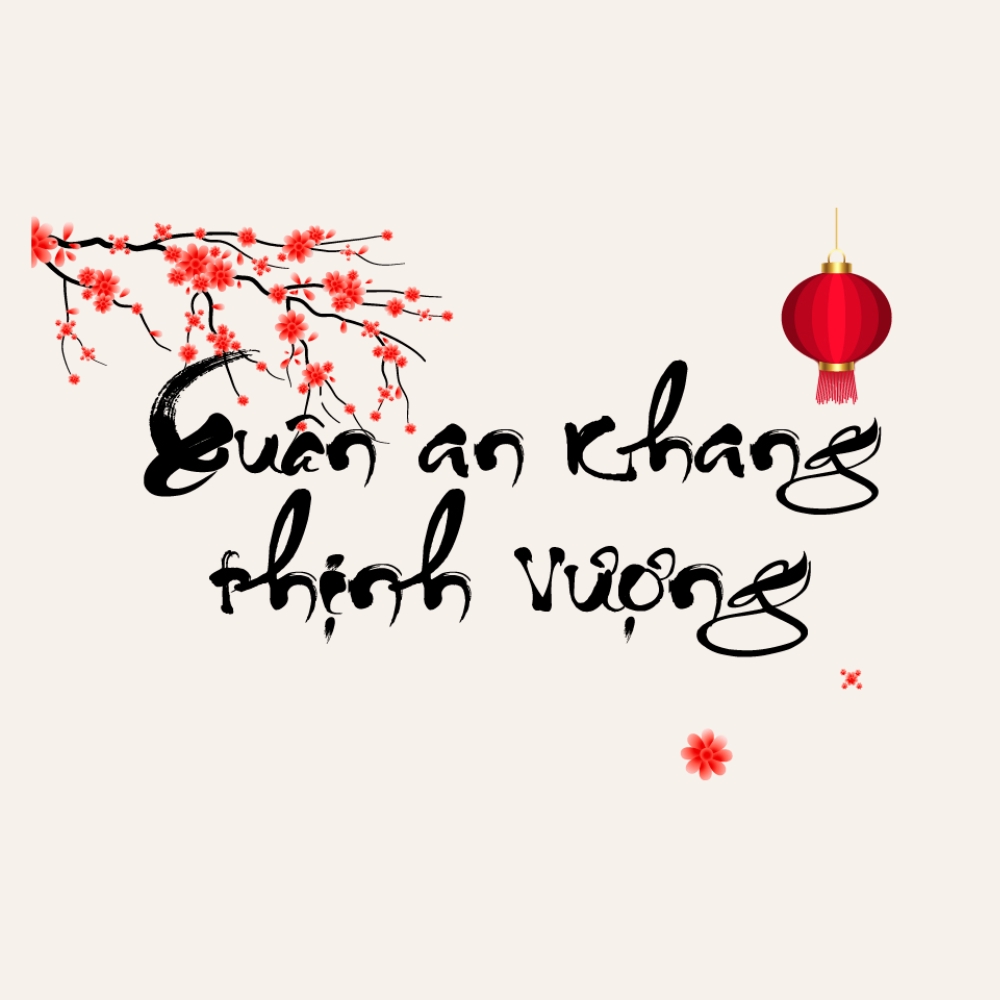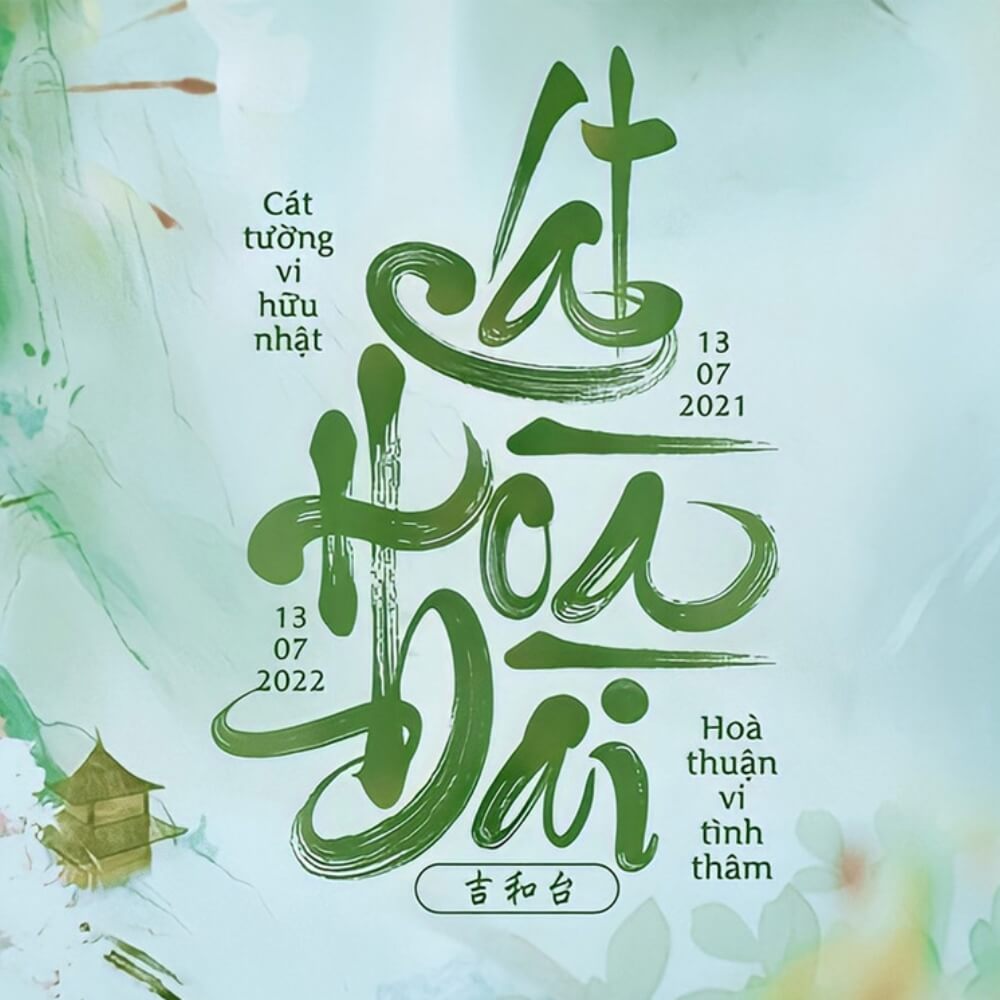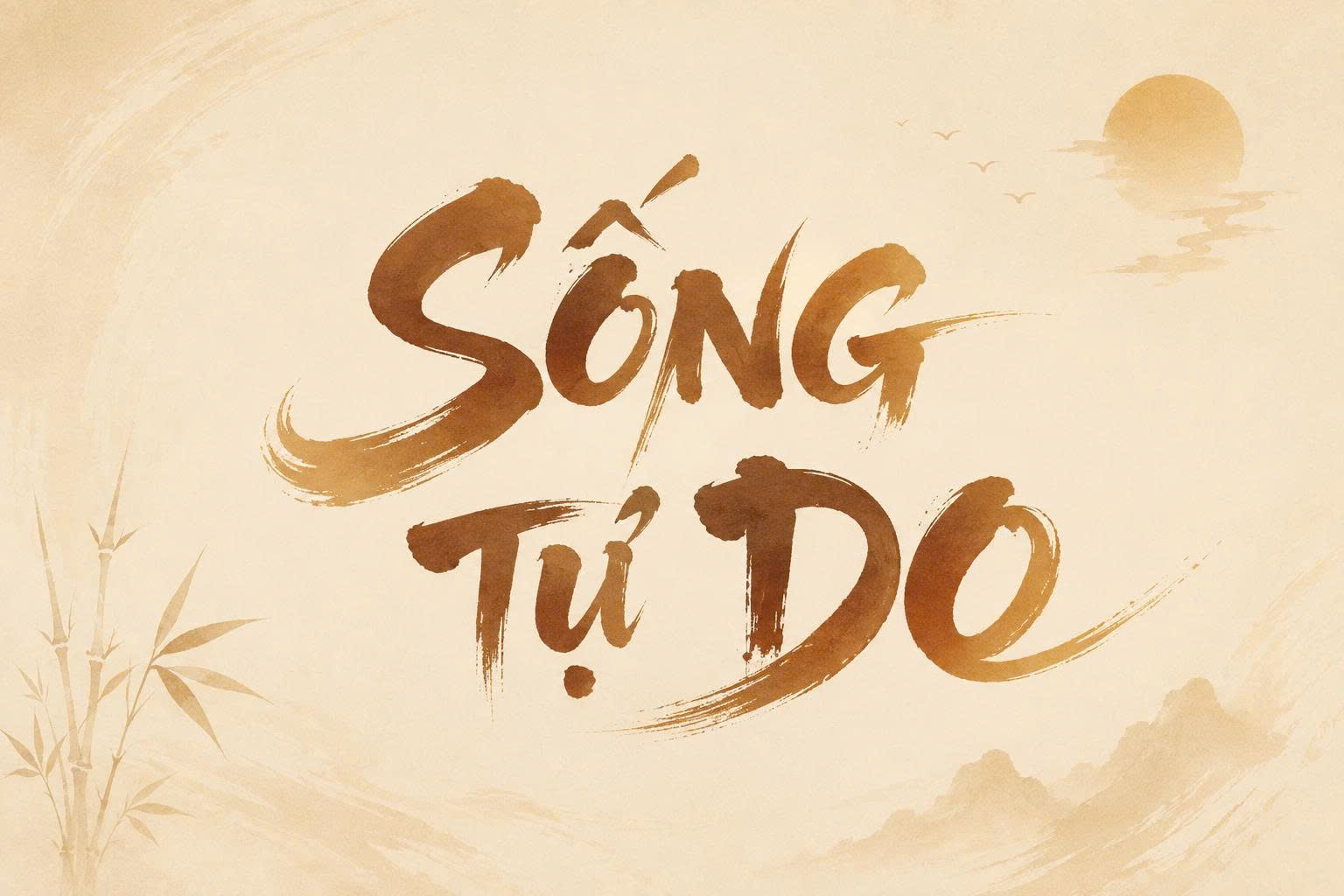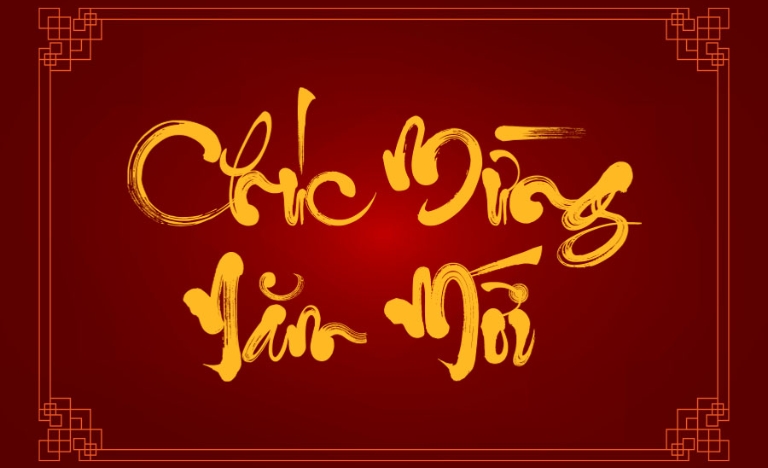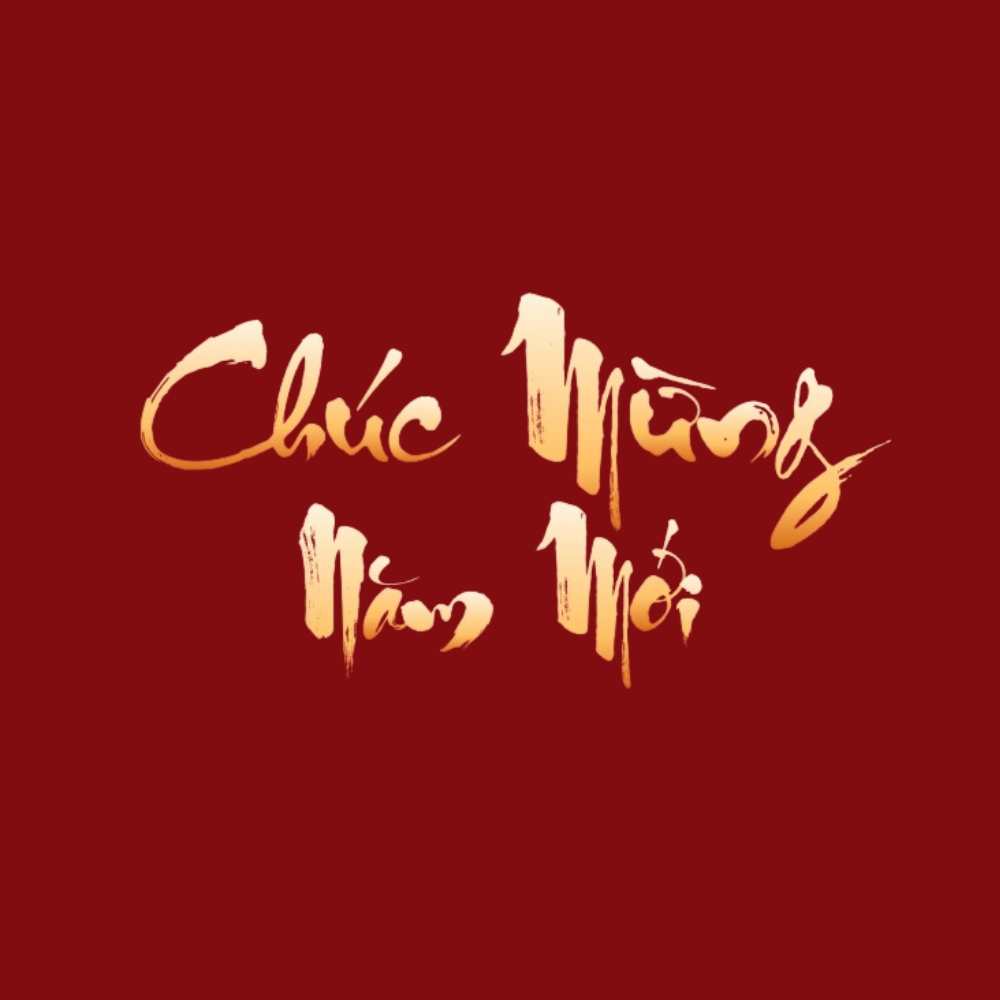
Font Việt hóa Thư pháp Đại tự là sự kết hợp giữa nét đẹp truyền thống của nghệ thuật thư pháp và tính tiện dụng của công nghệ thiết kế hiện đại. Với đặc điểm nét chữ to, mạnh mẽ và đầy tính biểu cảm, bộ font này thường được ưu tiên cho các dự án mang âm hưởng văn hóa hoặc các chi tiết trang trí đòi hỏi sự ấn tượng.
Nét đặc trưng đầy ấn tượng của font Việt hóa thư pháp đại tự
Dòng Thư pháp Đại tự thường gợi nhắc đến hình ảnh những nét cọ dày, mực đậm với các đường nhấn mạnh mẽ và dứt khoát. Phiên bản font Việt hóa Thư pháp Đại tự đã khéo léo xử lý các dấu thanh tiếng Việt sao cho không làm mất đi cấu trúc phóng khoáng của chữ gốc. Điều này giúp văn bản sau khi trình bày giữ được sự liền mạch, tránh cảm giác vụn vặt thường thấy ở những bộ font chưa được tối ưu hóa.
Bên cạnh yếu tố thẩm mỹ, cấu trúc của bộ font này còn tạo ra sự cân bằng giữa tính nghệ thuật và khả năng nhận diện. Dù các nét chữ có độ uốn lượn cao, người xem vẫn có thể dễ dàng nắm bắt được nội dung thông tin. Đây là lựa chọn phù hợp để tạo điểm nhấn cho những mảng tường trống, bảng tên khu nghỉ dưỡng hoặc các ấn phẩm truyền thông mang phong cách cổ điển.
| Phân loại phong cách | Calligraphy / Thư pháp Đại tự |
| Tính ứng dụng | Tiêu đề, bảng hiệu, trang trí nghệ thuật |
| Nguồn gốc | Đã được Việt hóa và tinh chỉnh dấu |
Lời khuyên thiết kế: Font Thư pháp Đại tự có nét chữ dày và chiếm diện tích. Khi sử dụng, bạn nên ưu tiên các tông màu có độ tương phản cao như đen, đỏ trên nền gỗ sáng màu hoặc giấy mỹ thuật để làm nổi bật vẻ đẹp của từng vệt cọ vẽ.
03 Ứng dụng font Việt hóa thư pháp đại tự trong không gian sống
Với vẻ ngoài đậm chất nghệ thuật, font chữ này mang lại giá trị thẩm mỹ cao khi được ứng dụng vào các hạng mục kiến trúc và trang trí nội thất:
- Bảng tên khu homestay và nhà vườn: Những nét chữ thư pháp uốn lượn rất ăn ý khi xuất hiện trên chất liệu gỗ hoặc đá. Đối với các dự án nhà lắp ghép mang phong cách nghỉ dưỡng, sử dụng font chữ này giúp không gian trở nên gần gũi và có chiều sâu văn hóa hơn.
- Trang trí không gian nội thất: Bạn có thể dùng font đại tự để thiết kế các câu trích dẫn, câu đối trang trí tại phòng khách hoặc khu vực sinh hoạt chung. Nét chữ mạnh mẽ sẽ tạo ra sự tương phản thú vị với phong cách kiến trúc hiện đại tối giản.
- Thiết kế bao bì và quà tặng: Đối với các chủ đầu tư kinh doanh sản phẩm đặc sản hoặc quà tặng truyền thống, font chữ thư pháp việt hóa đại tự giúp tăng giá trị nhận diện và tạo cảm giác chỉn chu cho sản phẩm.
03 Lưu ý để thiết kế hài hòa hơn với font Thư pháp Đại tự
Để khai thác hiệu quả vẻ đẹp của dòng font chữ đặc biệt này, người dùng nên lưu ý một số kinh nghiệm sau:
- Cân đối khoảng cách dòng và chữ: Do các nét chữ có xu hướng vươn dài và uốn lượn, bạn cần để khoảng cách thoáng giữa các dòng để tránh tình trạng các nét chồng chéo lên nhau gây khó đọc.
- Sử dụng làm điểm nhấn chính: Không nên dùng font Thư pháp Đại tự cho các đoạn văn bản dài hay thông số kỹ thuật xây dựng. Hãy để nó xuất hiện ở vị trí trung tâm như một tác phẩm nghệ thuật độc lập.
- Phối hợp font chữ: Sự kết hợp giữa font Thư pháp Đại tự (cho tiêu đề) và một font không chân (cho nội dung phụ) thường mang lại bố cục chuyên nghiệp, vừa giữ được nét truyền thống vừa mang hơi thở hiện đại.